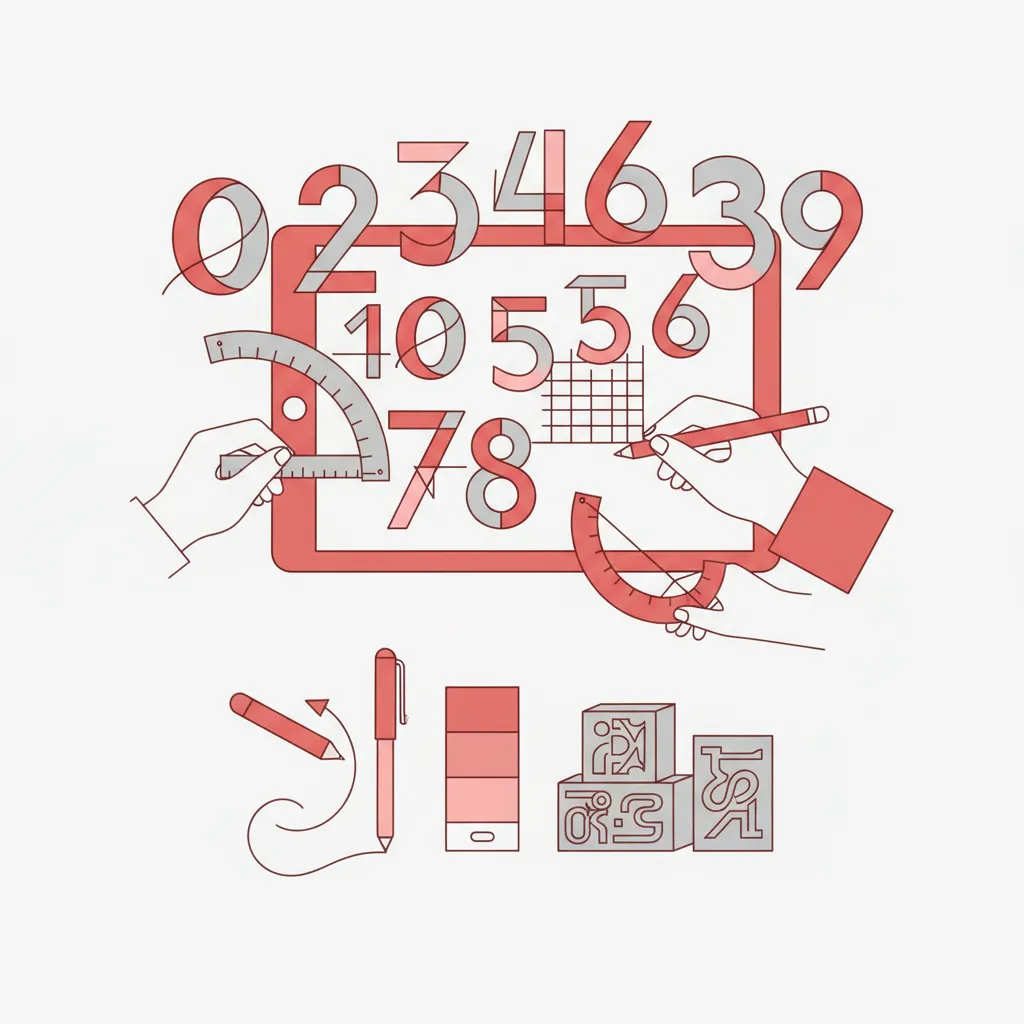
פונטים של מספרים שמשדרגים כל עיצוב
המעצבים מודאגים מאוד מהבחירה של הגופן לטקסט ולכותרות, אך לעיתים נדירות יותר הם מתמקדים בפונטים של מספרים. זו טעות יקרה. מספר שיוצג בגופן לא מתאים יכול לשבש את ההיררכיה החזותית של כל הדף, לבלבל את הקורא, ולהחליש את המסר של המותג. בין אם אתם מעצבים הזמנת חתונה, לוגו עסקי, כרזה לאירוע או ממשק דיגיטלי – פונטים של מספרים הם חלק בלתי נפרד מהשפה הטיפוגרפית שלכם. במדריך הזה נסביר מה הופך פונטים של מספרים למשפיעים, איך לבחור נכון לפי הצורך, ואיך להימנע מהטעויות שחוזרות שוב ושוב.
- פונטים של מספרים קיימים בשני סוגים עיקריים: Lining (מיושרים לשורת הבסיס) ו-Old-Style (עם עליות וירידות) – הבחירה ביניהם משפיעה ישירות על הטון העיצובי.
- גופן שתומך במספרים מלאים (Proportional) מתאים לטקסט רץ, בעוד Tabular Figures חיוני לטבלאות ונתונים מספריים.
- שילוב גרוע בין פונטים של מספרים לאותיות הוא אחת הטעויות הנפוצות ביותר – חובה לבדוק התאמה ויזואלית לפני הגשה סופית.
- לעיצובים קליגרפיים ורומנטיים, כמו הזמנות חתונה, הפונטים המתאימים ביותר הם אלה שמשלבים מספרים מסוגננים עם אותיות כתב יד.
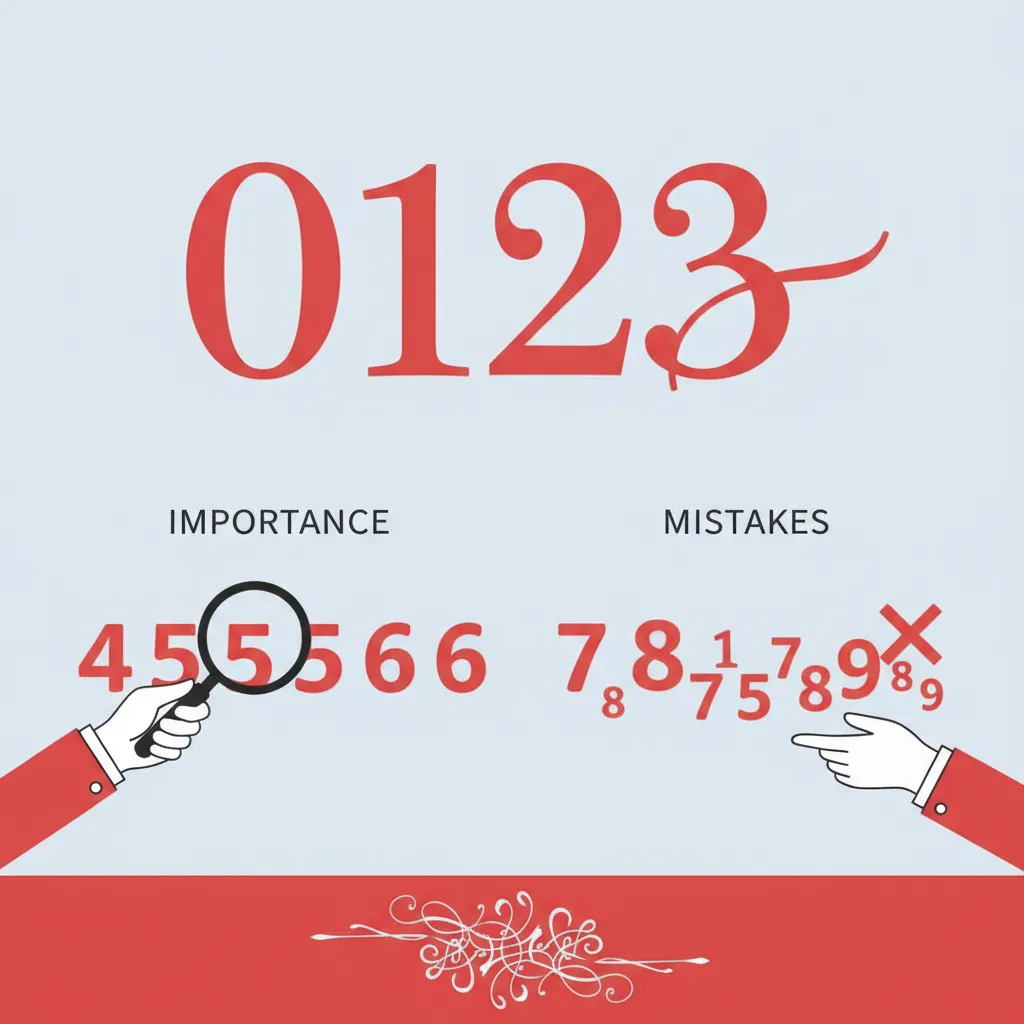
מה הם פונטים של מספרים ולמה הם חשובים?
פונטים של מספרים הם מערך הספרות שמעוצבות כחלק מגופן טיפוגרפי – ולכל גופן יש גרסת מספרים משלו, עם אופי ויזואלי ייחודי. בניגוד למה שחושבים רבים, לא כל גופן מייצר מספרים באותה איכות. ישנם גופנים שבהם המספרים מעוצבים בקפידה ומהווים חלק אינטגרלי מהשפה הטיפוגרפית, ואחרים שבהם המספרים נראים מוצמדים ולא שייכים.
בתחום ה-טיפוגרפיה הקלאסית קיימים שני סוגים עיקריים של פונטים של מספרים:
- Lining Figures (מספרים מיושרים) – כל הספרות בגובה אחיד, מיושרות לשורת הבסיס. מתאימות לכותרות, טבלאות ותצוגת נתונים.
- Old-Style Figures (מספרים קלאסיים) – ספרות עם עליות וירידות שונות, דומות לאותיות כתב יד. מעניקות מראה אלגנטי ומתאימות לטקסט רץ ולעיצובים קלאסיים.
בנוסף, ישנה הבחנה חשובה בין Proportional Figures – מספרים עם רוחב משתנה לפי הספרה – לבין Tabular Figures – מספרים ברוחב אחיד, הכרחיים לטבלאות ודוחות כספיים. ב-Google Fonts ניתן לבדוק את תמיכת הגופן בסוגי מספרים שונים לפני שמורידים אותו.
לפי עקרונות ה-UX Research, בחירת פונטים של מספרים שאינה עקבית עם שאר הגופן עלולה לפגוע בקריאות ולהוסיף "רעש ויזואלי" שמפריע לתקשורת המסר. כאשר מעצבים בוחרים פונטים של מספרים בתשומת לב, הם יוצרים עיצוב שלם ומלוכד יותר.
איך לבחור פונטים של מספרים לפי סוג הפרויקט?
הבחירה הנכונה של פונטים של מספרים תלויה ישירות בסוג הפרויקט ובמסר שרוצים להעביר. אין "פונט מספרים אוניברסלי" – כל הקשר עיצובי דורש גישה שונה.
עיצובים רומנטיים ואירועים מיוחדים
להזמנות חתונה, שילוטים לאירועים ועיצובי "שמרו את התאריך", פונטים של מספרים צריכים להתאים לסגנון הקליגרפי של הטקסט. גופן כמו פונט ז׳ולייט, שהוא פונט קליגרפי עברי רומנטי, מדגים כיצד ניתן לשלב מספרים שמשתלבים בחלקה עם אותיות הסקריפט – ויוצרים הרמוניה ויזואלית מלאה.
מיתוג עסקי ולוגואים
למיתוג עסקי, פונטים של מספרים צריכים לשדר מקצועיות ואמינות. גופנים מסוג Sans-Serif עם Tabular Figures מתאימים לדוחות, מחירונים וממשקים דיגיטליים. לעומת זאת, לוגו שמכיל מספר (שנת ייסוד, ספרה מזהה) דורש פונט מספרים שמתאים לאופי הגרפי הכולל. כדאי לבחון את עקרונות עיצוב גופן עברי כדי להבין כיצד אופי הגופן משפיע על תפיסת המותג.
עיצוב דיגיטלי ואפליקציות
בממשקים דיגיטליים, פונטים של מספרים חייבים להיות קריאים גם בגדלים קטנים. Tabular Figures הם כמעט חובה כאשר מציגים נתונים בטבלאות, שעונים, מחשבונים או לוחות מחירים. גופן כמו פונט דיפלומט – שמציע מגוון משקלים ותמיכה בטקסט רץ – הוא דוגמה לגופן שבו פונטים של מספרים מעוצבים לתמוך גם בתצוגה דיגיטלית.
טיפים מקצועיים לשימוש בפונטים של מספרים
מניסיון עם מגוון פרויקטים עיצוביים, ישנם כמה כללי אצבע שחוסכים הרבה תיקונים מיותרים בשלב הגמר:
- ✓ בדקו את המספרים לפני הבחירה הסופית – הציגו את הספרות 0 – 9 בגודל השימוש בפועל, לא רק טקסט לדוגמה.
- ✓ ודאו שהמספרים מתאימים לאותיות – בדקו התאמה ויזואלית בין פונטים של מספרים לאותיות הגופן, במיוחד בגובה x-height.
- ✓ בחרו Tabular Figures לנתונים – כל עמודת מספרים בטבלה חייבת להיות ברוחב אחיד למראה מסודר.
- ✓ אל תשתמשו בגופן שונה רק למספרים – אלא אם יש סיבה עיצובית מכוונת, שמרו על עקביות בתוך הפרויקט.
- ✓ בחנו את פונטים של מספרים על רקעים שונים – מספרים בצבעים בהירים על רקע כהה מתנהגים אחרת מאשר הפוך.
תהליך בחירת פונטים של מספרים ב-4 שלבים
שלב 1: הגדירו את ההקשר
האם המספרים מופיעים בטקסט רץ, בכותרת, בטבלה, או כאלמנט עיצובי עצמאי? ההקשר קובע את סוג פונטים של מספרים הנדרש.
שלב 2: בחרו את סוג הגופן
Lining לכותרות ותצוגת נתונים, Old-Style לטקסט ספרותי ואלגנטי, Tabular לטבלאות ומחשבונים.
שלב 3: בדקו התאמה לשאר הגופן
הציגו את המספרים לצד האותיות בפרויקט. שימו לב לגובה, לעובי הקו ולאופי הכללי – האם הם משתלבים?
שלב 4: בחנו בתנאים אמיתיים
ייצאו פרופ, הציגו על מסך ועל הדפסה. פונטים של מספרים שנראים טוב בתצוגת עריכה עשויים להיראות שונה לחלוטין בפרויקט הסופי.
⚡ נקודת מפתח:
- גופנים עם תמיכה מלאה ב-OpenType מאפשרים בחירה בין סוגי מספרים שונים ישירות מתוך תוכנת העיצוב – ללא צורך בגופן נפרד.
- בגופנים עבריים, פונטים של מספרים מערביים (לטיניים) הם אלה שמשמשים בפועל – לכן חשוב לבדוק את ההתאמה הויזואלית גם עבורם.
טעויות נפוצות בפונטים של מספרים ואיך להימנע מהן
גם מעצבים מנוסים נופלים בפחים הבאים כשמדובר בפונטים של מספרים. הנה הטעויות הנפוצות ביותר – ואיך לתקן אותן:
רעיונות ליישום מיידי:
- בחנו פרויקט קיים – פתחו עיצוב שכבר השלמתם ובדקו ספציפית את פונטים של מספרים. האם הם מתאימים לגופן? האם הם Tabular במקומות הנכונים?
- צרו דף בדיקה – שמרו תבנית עם הספרות 0 – 9 בכל גודל שימוש, לבדיקה מהירה בכל פרויקט חדש.
- נסו גופן חדש – בחרו גופן שמוצא חן בעיניכם ובדקו את פונטים של מספרים שלו ספציפית – לעתים תגלו שם אופי ויזואלי מפתיע.